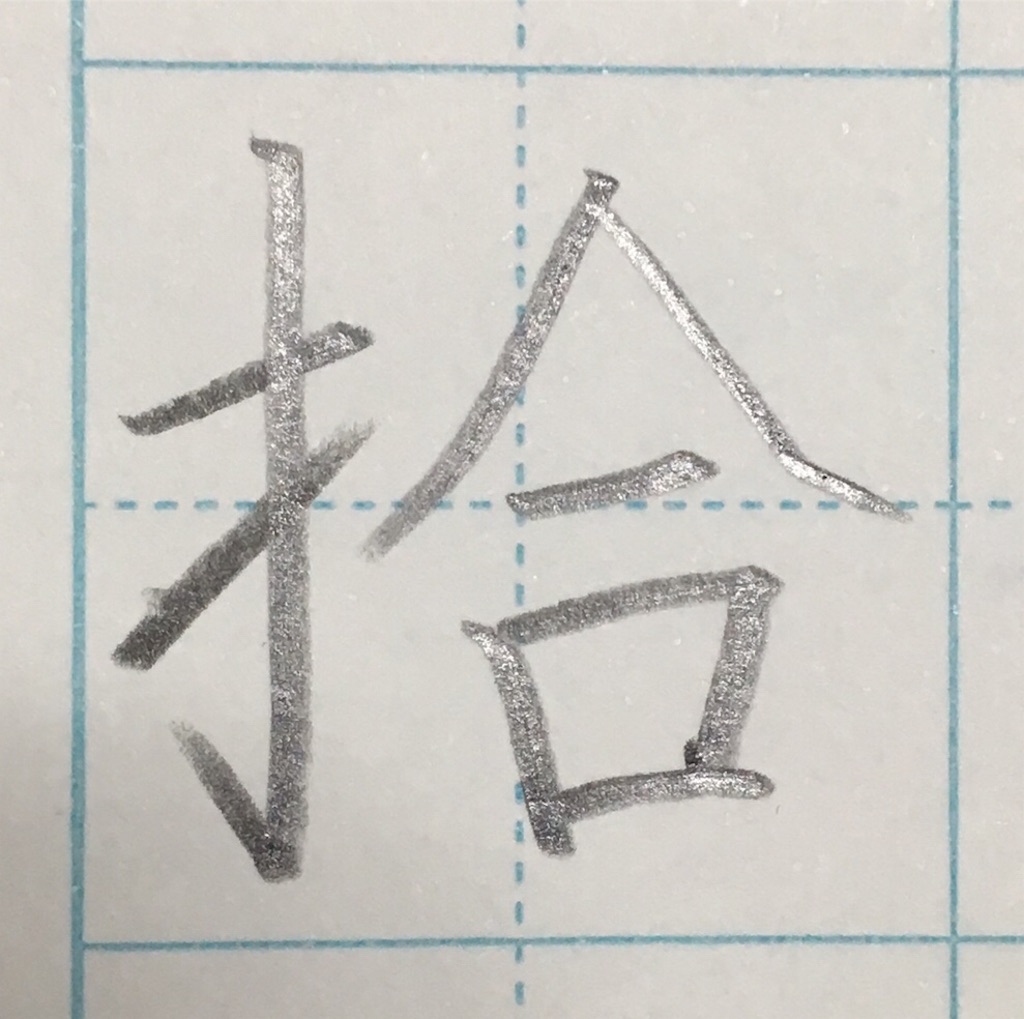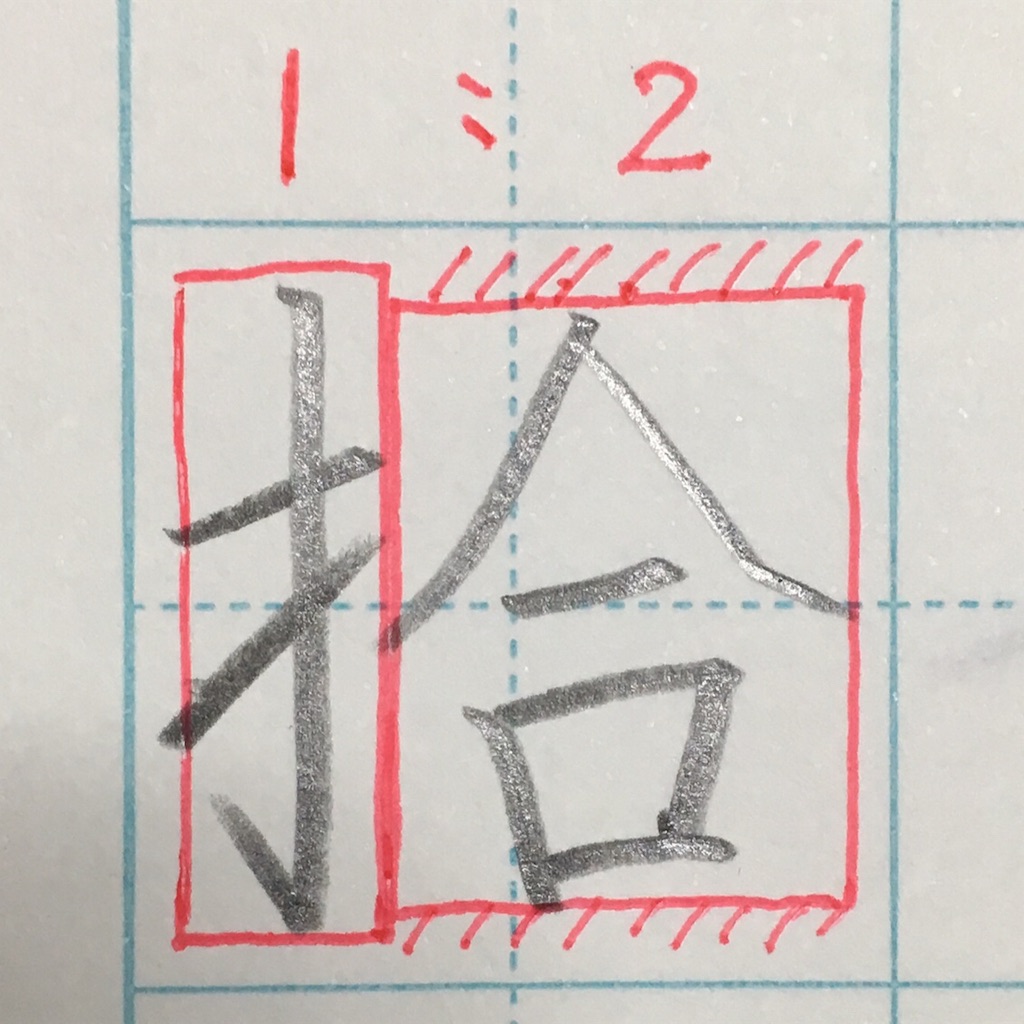
今回は「拾」の書き方を解説します。
「拾」のきれいな書き方
「拾」の細かいポイント
「てへん」
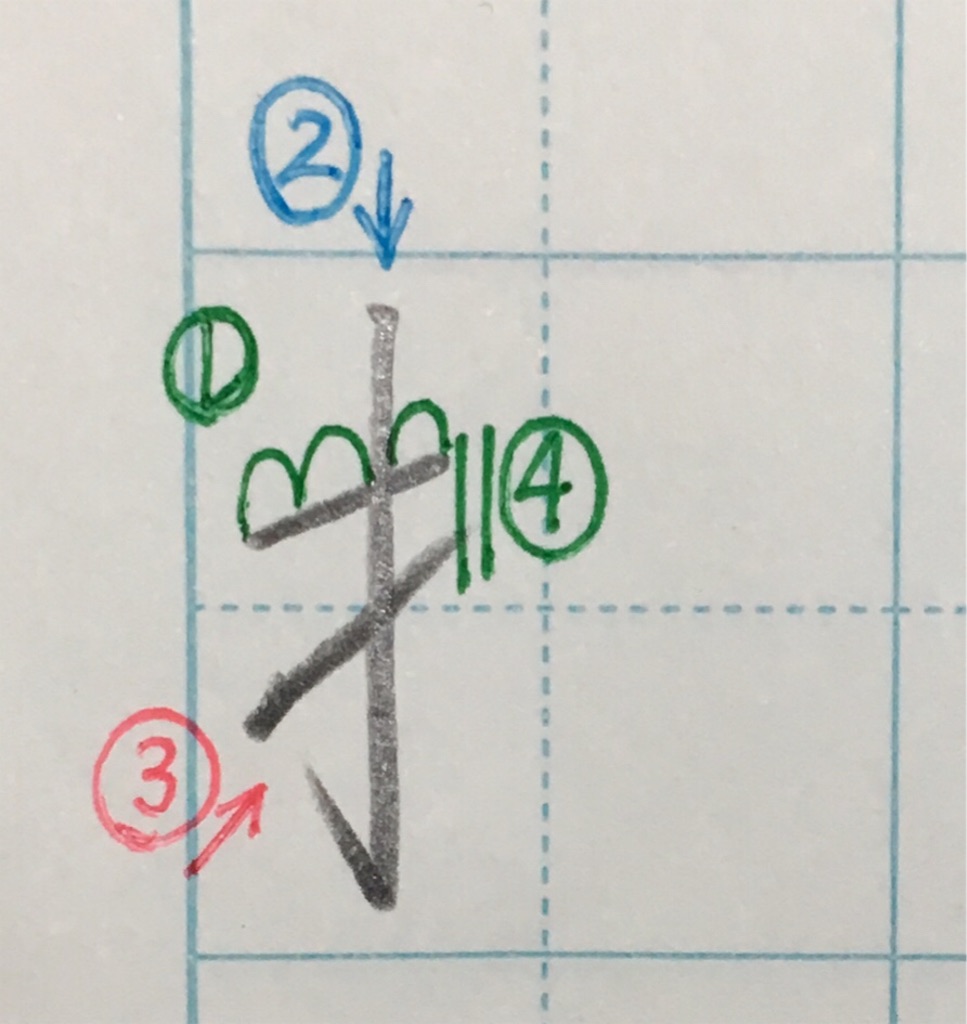
①1画目は縦画と1:2で交わる。
②まっすぐ!曲がらない!
③思い切って右上がりに「シュっ」と払い上げる。
④右端は揃える。
「合」
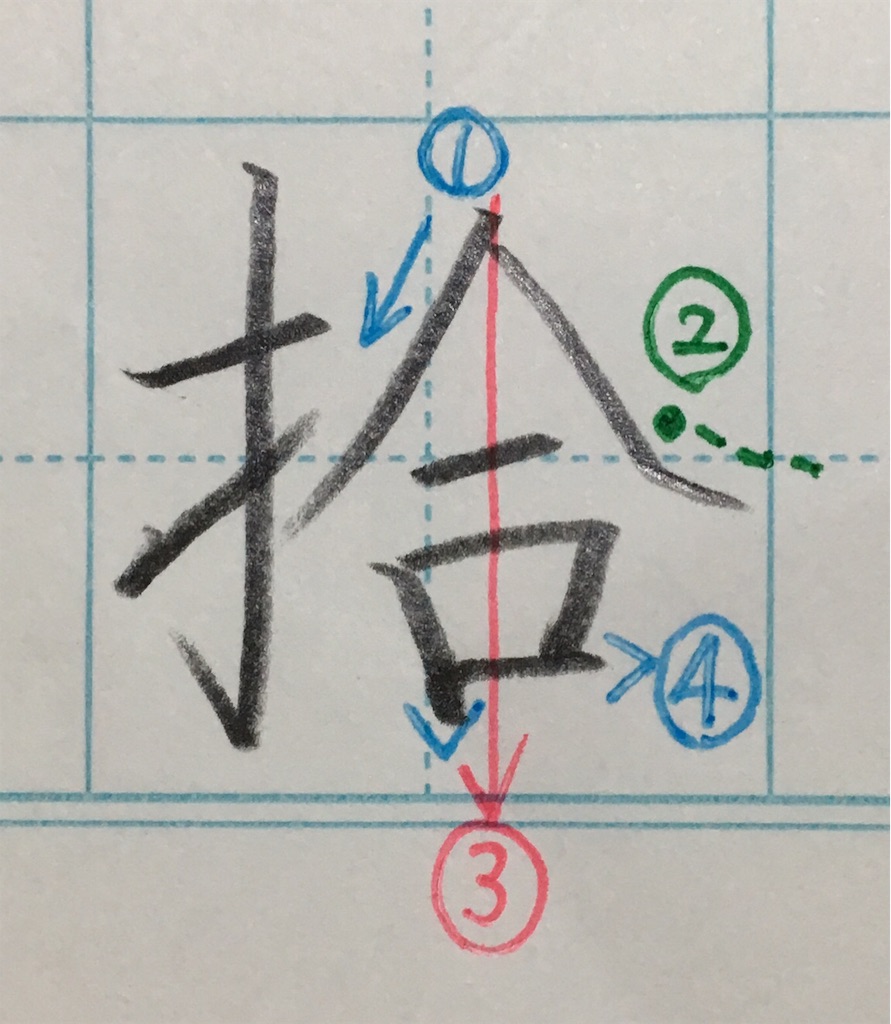
①「てへん」にうまくはめこむように払うと◎。
②止めて、払う。
③中心を意識する。
☆4画目のはじめ、6画目&口の中心を通るように。
☆なんだかんだで、4画目の書き始めが一番大事かも…。